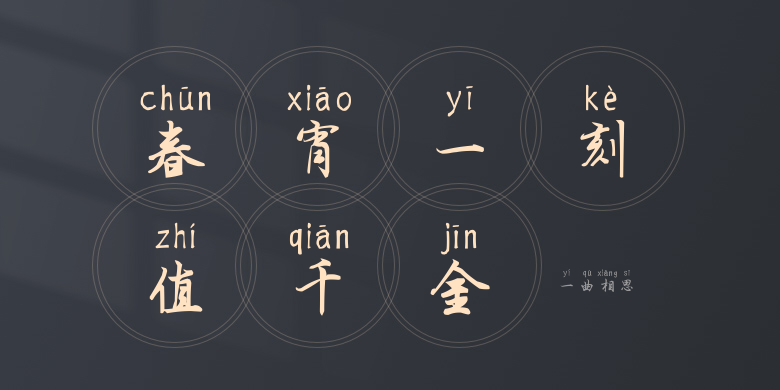
一曲相思
一曲相思,这款字体结构工整、笔画清晰,兼顾美观与易读性,适用于标题、正文、海报、包装、LOGO 等多种场景。字形优雅稳定,风格百搭耐看,适配日常排版与创意设计,让文字呈现更舒适、更具质感。一曲相思一笔一画,皆是细节,以均衡的比例、流畅的线条打造舒适视觉体验,字形端正大气,风格简约现代。无论是商业设计、品牌宣传还是日常排版,都能轻松驾驭,让文字更有格调与力量。一曲相思字体下载。